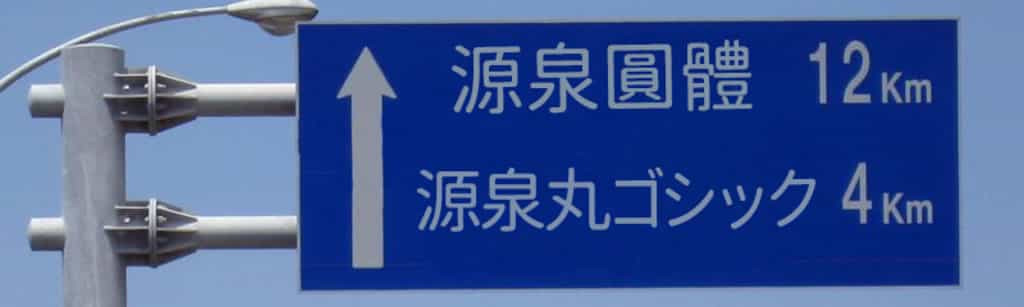
麥克筆手寫風格中文字型「貓啃什錦黑」,免費開源且可商業使用
貓啃什錦黑(Maoken Assorted Sans-TC)是一個免費開放原始碼的繁體中文字體,主要改作自日本作者波間のかけひき創作的「にしき的フォント」(Nishiki-teki)字型。此字體根據《常用國字標準字體表》與 jf 7000 當務字集等多種來源,增補了繁體中文常用字,並針對部分漢字筆劃進行最佳化與修改,保留了日文字體的原有風格,以更符合中文使用者的需求。字體採用麥克筆手寫風格,筆劃活潑生動,呈現出可愛且有趣的視覺效果,非常適合用於海報或宣傳品的設計中,能有效吸引視覺焦點。此外,貓啃什錦黑採用 SIL Open Font License 1.1 授權,允許免費下載並自由使用,無須告知或標示原作者,亦可用於商業用途。
苦累蛙圓體 Kurewa Gothic:原子筆手寫風格中文字體,五種字重免費可商用
「苦累蛙圓體」是一個源於日文「紅道字體」的補字字型。紅道字體是一種具有手寫風格的日文字體,設計上省略了類似畫筆的元素,只保留字母的骨架,營造出原子筆手寫字母的印象。根據作者的說明,苦累蛙圓體與原作的主要差異在於調整了部件寫法,不僅補足繁體中文常用字的缺字,還增加了 Light、DemiLight、Regular、SemiBold 及 Bold 共五個字重。此外,它還將針對日本設計的全形標點符號調整為台灣常見的置中用法,並增加了臺灣閩南語和客語的部分中文字。「苦累蛙圓體」採用 SIL Open Font License 1.1 授權,允許免費商用並可自由優化與改作。
匯文築地五號明朝體:復刻民國早期舊鉛字字體,繁體中文免費商用
「匯文築地五號明朝體」是一個掃描日本昭和11年(1936年)東京築地活版製造所出版的《改正五號活字總數見本 全》這本冊子而成的字體,其字型是現在日本明朝體之源流和當時中國的鉛字字型一樣相似,兩者都源自於康熙字典的字型。根據作者自述,整個字型除了收錄了冊子內的字體外,還收錄所有平假名、片假名和 241個萬葉假名跟變體假名。然後補了西文字母還有一些圖形符號,共收錄 9262個字符,但未包含簡體字和日本新字型,不保證不缺字,但足以應付一般日常使用。
MiSans Global:小米全球語言字體專案,免費商用支援繁體中文
MiSans Global 是由小米主導的全球語言字體專案,與蒙納字庫和漢儀字庫合作打造。這個字體家族覆蓋 20 多種書寫系統,支援超過 600 種語言,擁有逾 10 萬個字元。MiSans Global 的設計強調簡約清晰、人文易讀、統一的視覺風格。所有字型可免費在任何平台和商業項目中使用,並支援自由調整字型外觀粗細和間距等功能。此外,網站提供了線上預覽功能,讓使用者即時想要預覽的文字,並調整字重與字體大小。MiSans Global 為使用者提供可以一鍵全部下載,或單獨選擇字型進行下載。
源泉圓體:繁體中文字型,提供六種字重,免費可商用
「源泉圓體」是源於思源黑體的開放原始碼中文字型。根據作者的自述,就是把筆畫全改圓,將黑體的腳盡可能拔除,並加上封閉區域的內圓角處理,盡可能去逼近圓體樣貌,整體看起來會比一般的圓體看起來更為工整與方正。「源泉圓體」以開放原始碼的形式在 GitHub 平台上提供,供有需要的使用者免費下載。源泉圓體的特點在於涵蓋了幾乎所有常見的字元,同時支援繁體中文和日文。不論使用的是 Windows 或 Mac 作業系統,都可以輕鬆地進行下載和安裝。此外,在授權上亦基於 SIL Open Font License 1.1 授權條款公開發布,所以可自由使用,不限個人或商業用途。
Public Sans 美國政府設計的開放原始碼英文字型,可自由下載和使用
Public Sans 是由美國政府出資設計的免費字型,在此之前多半使用外部開源字型像是 Source Sans Pro 和 Roboto,這個新字型出現是 GSA 促進自定義字型使用的一部分,在品牌識別上也會更為清楚。因為是修改自 Libre Franklin Font 因此沿用相同的 SIL Open Font License v1.1 授權
Public Sans 被設計為一種漸進增強的網路字體,並且能夠與 Apple 和 Google 系統字體良好配合,提供 font-weight 從 100 至 900 並包含斜體(italic),因此,無論在標題、內文或使用者介面都能有非常好的表現,在細節方面,Public Sans 將筆劃粗細規則化、非圓角頂點及使用更一致的曲線,提高在不同螢幕大小裝置上的易讀性。
台北黑體:適合文字編排、平面設計、影音字幕使用的繁體中文免費字型
台北黑體是基於思源黑體進行調整的黑體字型,由「翰字鑄造」(JT Foundry)著手改良,讓思源黑體更適於印刷使用。翰字鑄造提出時下免費的繁體中文字型大多符合台灣及香港的教育部門標準,不盡然適合印刷。台北黑體在以思源黑體作為基礎下改善一些部件寫法,維持漢字的對稱之美,並持續讓字符也保有漢字結構的平穩和剛直,當然更重要的是讓印刷用字型維持印刷體的樣貌。
Taiwan Icon Font:用圖示字型展現台灣之美
Taiwan Icon Font 是一套充滿台灣在地特色的免費圖示字型,由居住在台南的日本設計師 holoko 與旅居台灣的英國程式設計師 Rob 攜手開發。這個跨國合作的設計團隊,以「台灣旅遊」為創作主軸,精心設計出眾多台灣旅遊景點的專屬圖示。其涵蓋範圍廣泛,不僅包含台灣著名地標如台北 101、中正紀念堂,更融入了深具台灣文化特色的元素,如香醇的珍珠奶茶、經典的台灣啤酒,以及便民的捷運系統和 YouBike 共享單車等,完整呈現台灣從觀光到生活的多元面貌。